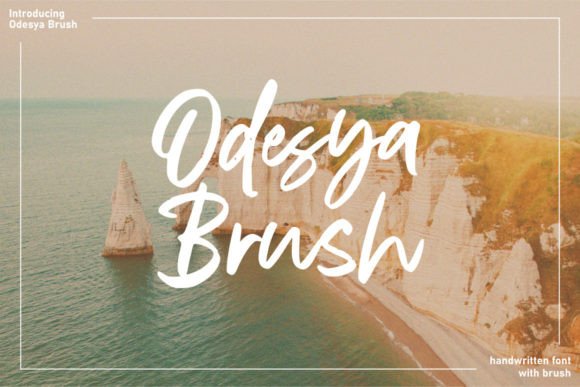
Odesya Brush
Odesya Brush: A Fonte Assinatura que Eleva Seu Design
Se você busca elegância e sofisticação para projetos de branding, embalagens ou qualquer peça de alta qualidade, a Odesya Brush chega como a escolha ideal. Essa fonte assinatura combina traços clássicos com curvas graciosas, proporcionando um visual atemporal que se destaca em diversas aplicações.
- Design clássico e moderno – Letras bem proporcionadas que unem tradição e contemporaneidade.
- Curvas suaves – Cada traço foi pensado para garantir fluidez e legibilidade, mesmo em tamanhos pequenos.
- Versatilidade de uso – Ideal para logos, rótulos de produtos premium, convites de casamento, e materiais de marketing de luxo.
- Impacto visual – A presença marcante da Odesya Brush confere um toque de exclusividade e refinamento à sua marca.
Ao escolher Odesya Brush, você garante que sua identidade visual transmita confiança e elegância, criando uma conexão emocional com o público alvo. Experimente hoje mesmo e descubra como essa fonte pode transformar seu projeto em uma obra‑de‑arte de alto padrão.